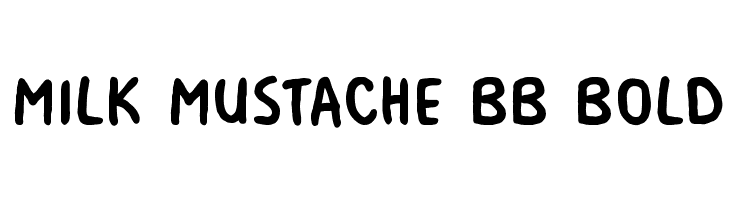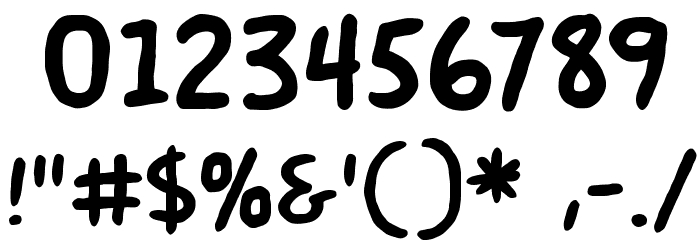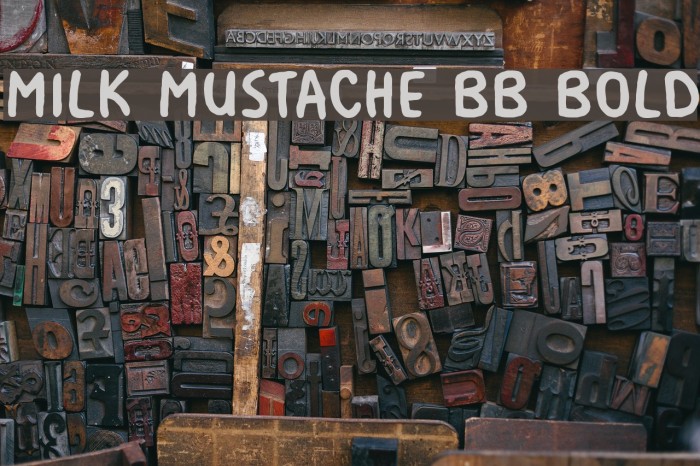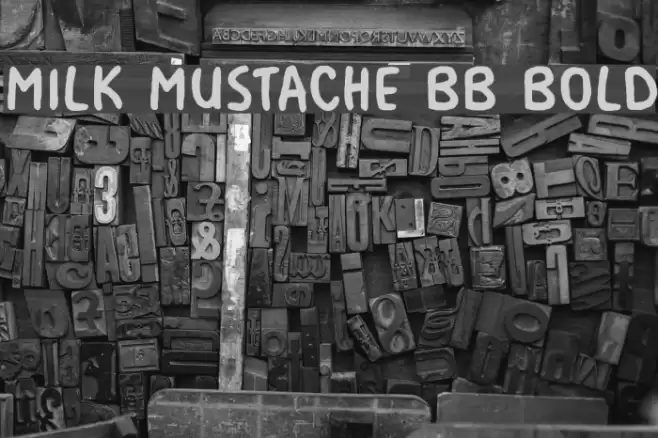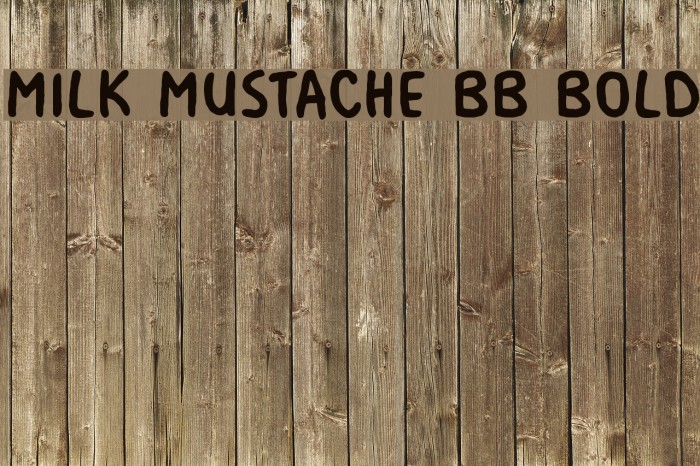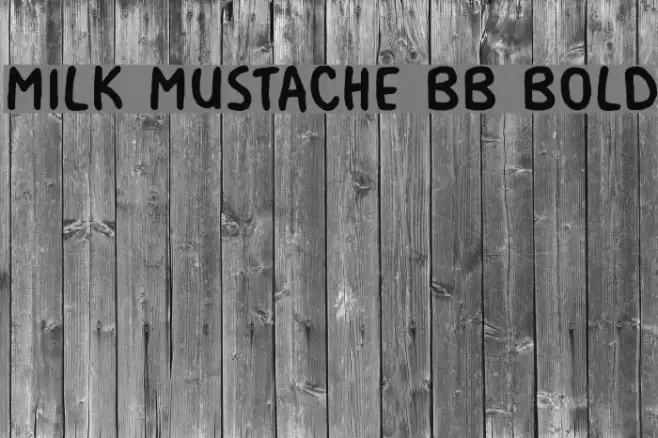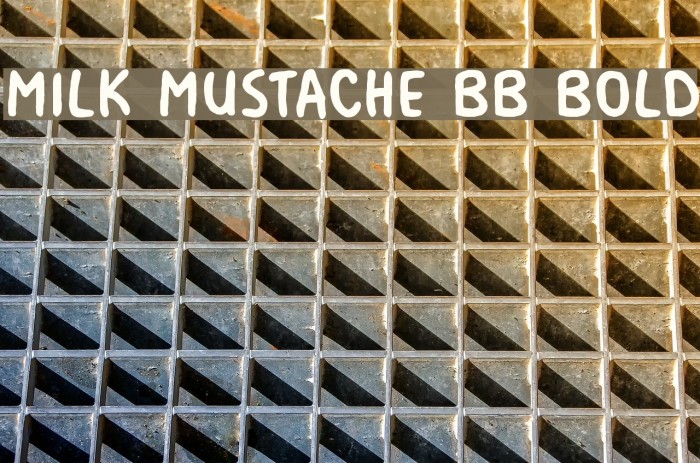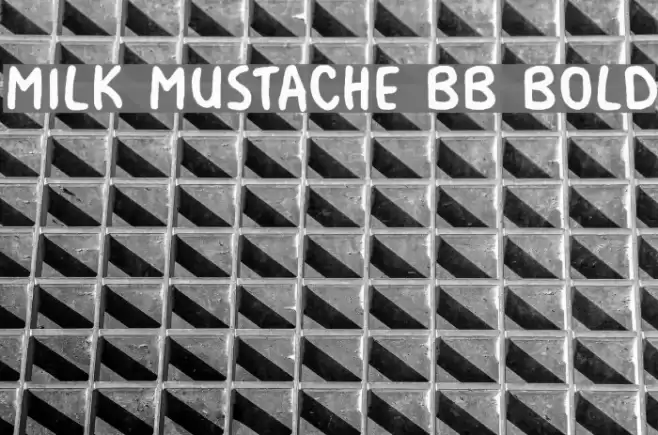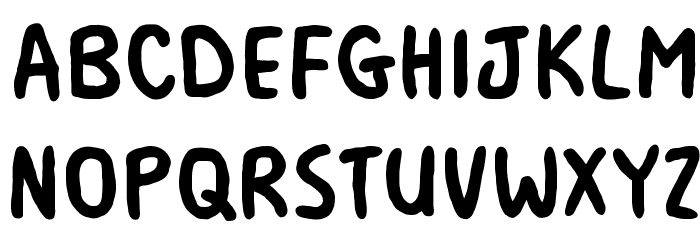
Milk Mustache BB Bold Font
Fonts by www.blambot.com
| Proiecte propuse | Ideal for children's books, playful branding, casual invitations, and creative posters. |